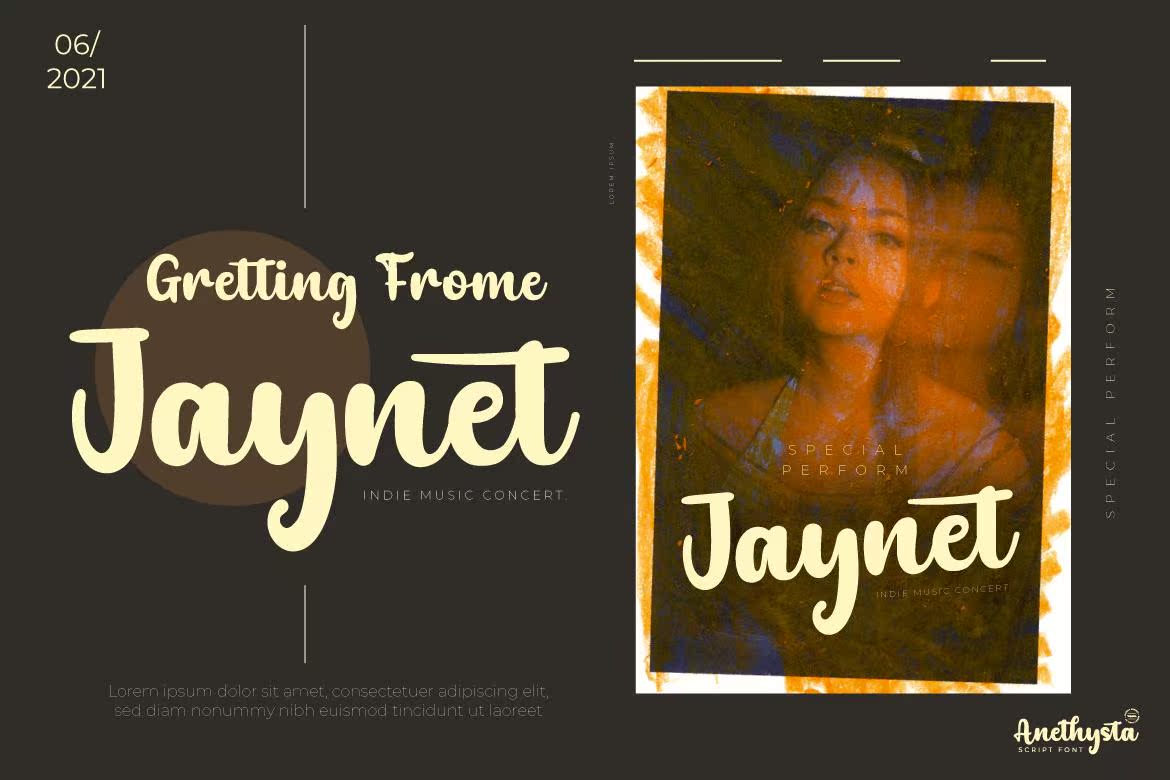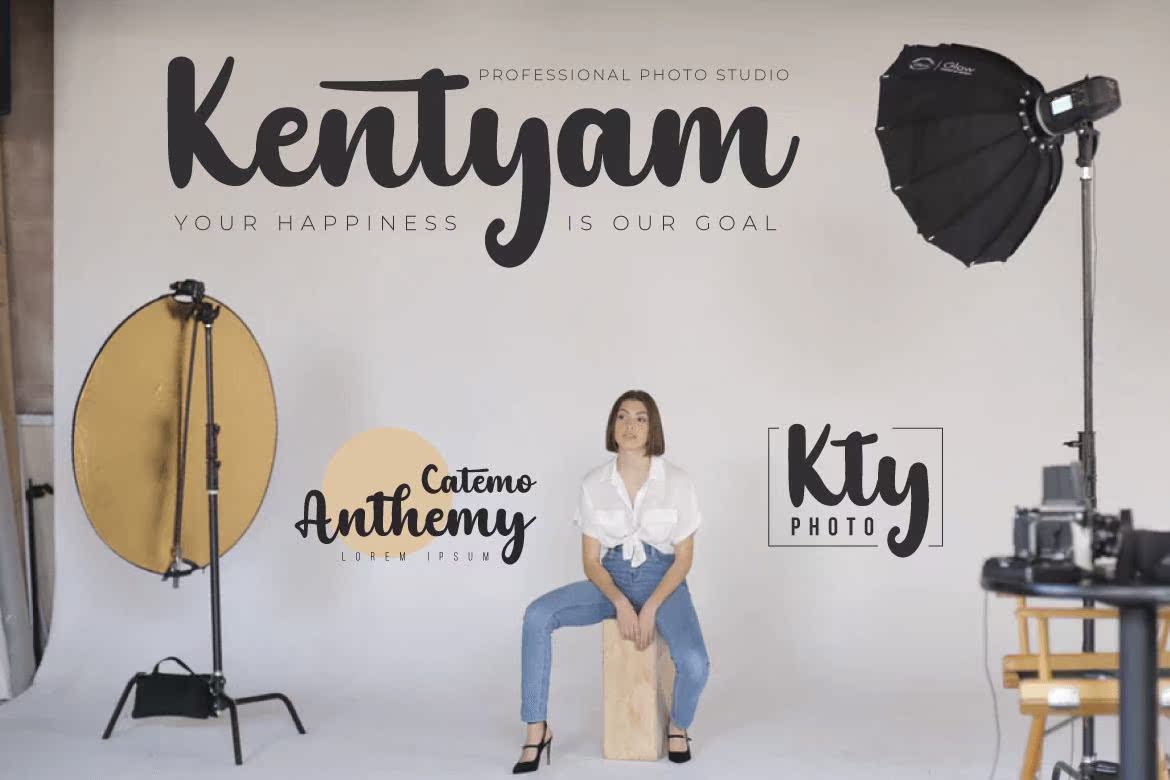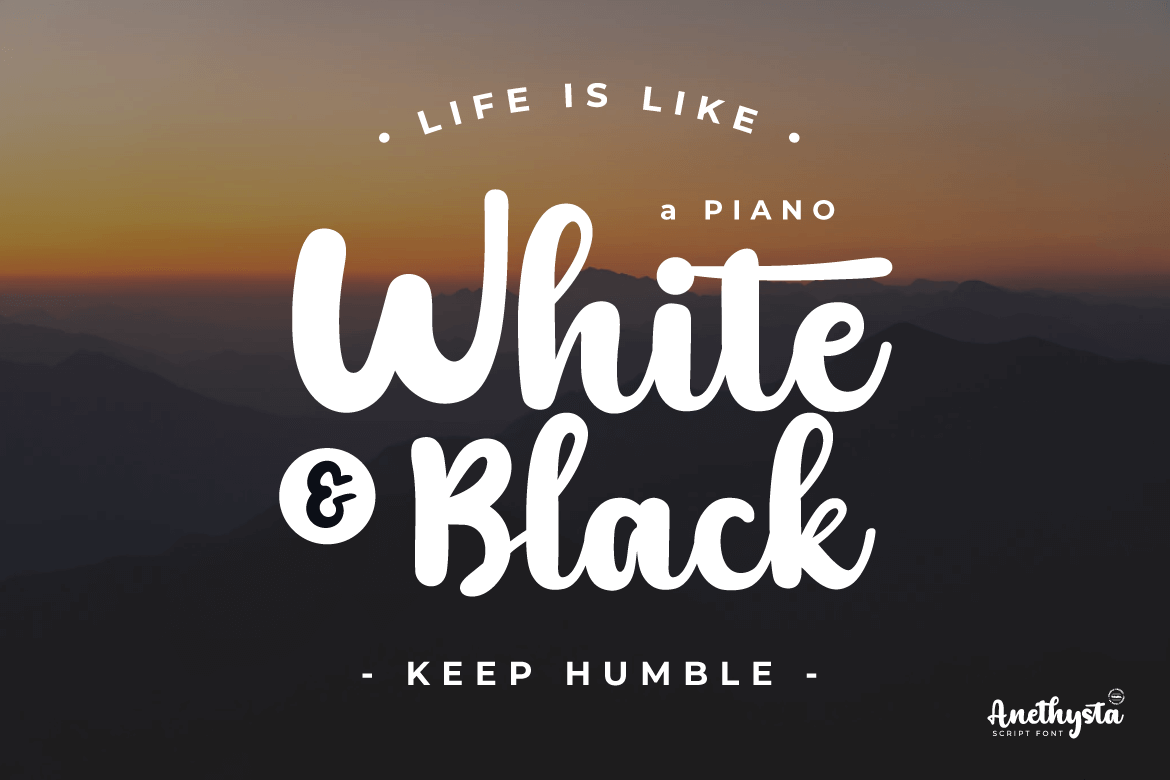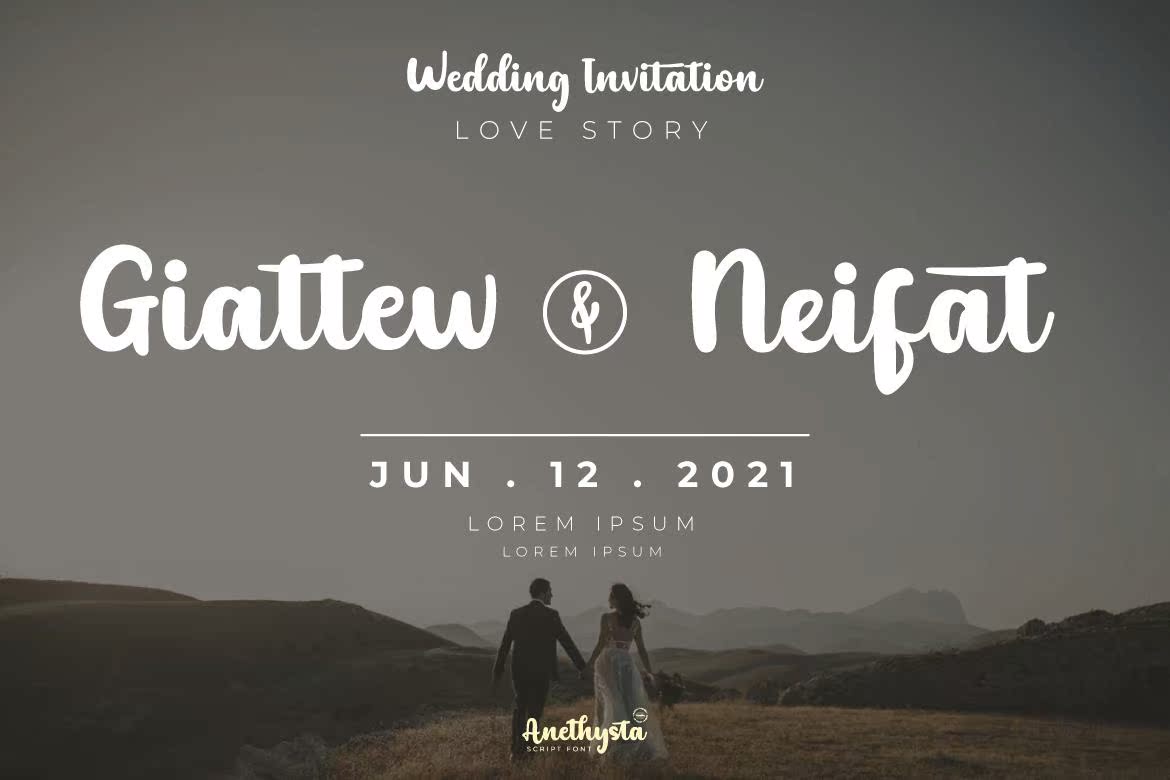
Anethysta是一款授权的粗体书写字体,可在各种项目之前灵活使用,使用该字体时,女性的新发型将保持优雅,这种字体有独特的和不同的压力,但仍然很漂亮。当所有的观众都看到它时,它的自然和书写给人留下了生动的印象。这种字体的设计考虑到了适合你需要的比例和成分,也设计了Anatural和Touch,具有交替的特征,韧带鞋带支持多种语言,因此这种字体适用于工艺品,户外活动、标识类型、海报、标题、横幅、婚礼宣传、产品包装标识、报价、社交媒体封面、书皮等。Anethysta是一款授权的粗体脚本字体,用于展示和灵活处理俄罗斯各种项目、女性模特儿。使用该字体时,该字体将保持不雅,这种字体有独特的和不同的压力,但仍然很漂亮。当所有的观众都看到它时,它的自然和书写给人留下了生动的印象。这种字体的设计考虑到了适合你需要的比例和成分,也设计了Anatural和Touch,具有交替的特征,韧带鞋带支持多种语言,因此这种字体适用于工艺品,户外活动、标识、海报、标题、横幅、婚礼宣传、产品包装标识、报价、社交媒体封面、书皮等。